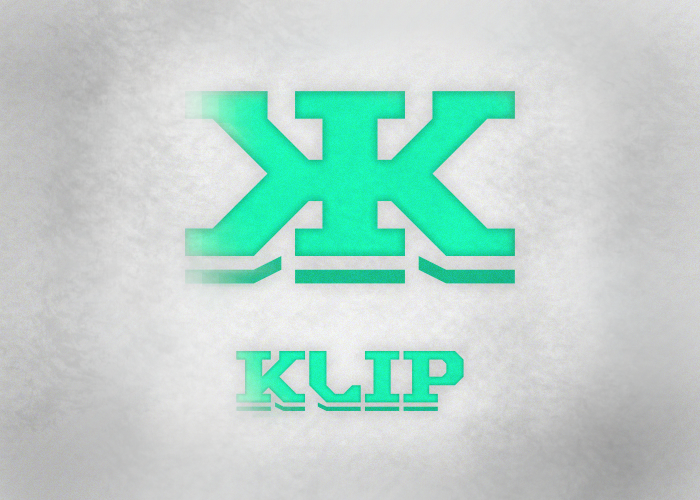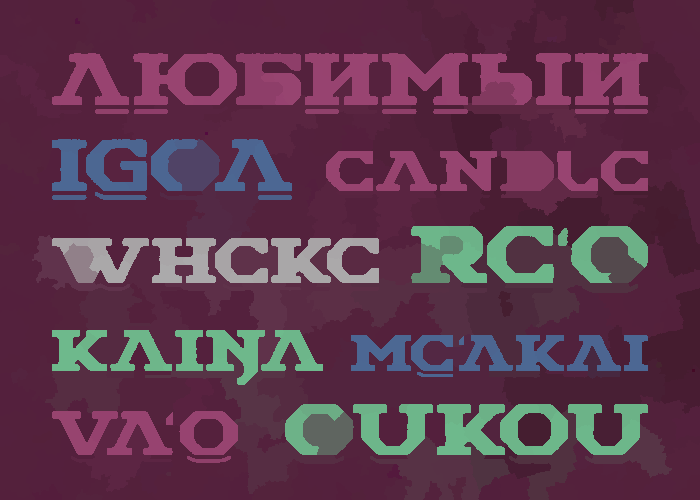
Мне нравится, и интересные эффекты на примерах использования. Некоторые буквы делают шрифт футуристичным, хотя такой шрифт с засечками сам по себе старинный и напиоминает мне ещё шрифт спортивных команд или общин в американских колледжах, поэтому тут бы хорошо смотрелись ещё греческие буквы.
nice! like the shadowy things at the bottom
Мне нравится, и интересные эффекты на примерах использования. Некоторые буквы делают шрифт футуристичным, хотя такой шрифт с засечками сам по себе старинный и напиоминает мне ещё шрифт спортивных команд или общин в американских колледжах, поэтому тут бы хорошо смотрелись ещё греческие буквы.
Дааа, я пыталая подражать виду шрифтах тех американских общин. А конечно, мне нужно, чтобы было футуристично)))
И спасибо) Я сделал тот эффект случайно, а подумал, что смотрелся хорошо))